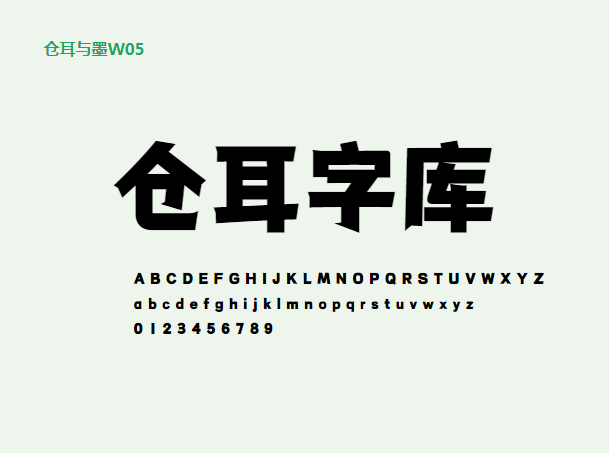
倉耳與墨是一款包含5個字重的家族字體,風格偏向現代創意字體,強調厚重與力量,具有醒目、有力和前衛的特點。
字體將篆刻的“刀意”融入其中,在筆形處理時模擬了類似篆刻的刀刻痕跡,同時為中和這種“尖銳”,在轉折和“口”字結構上使用圓轉角的處理方法,讓整個字內方外圓。配套使用的英文和標點部分也同步沿用了與中文相同的設計特點,在混排時風格統一,不會突兀。